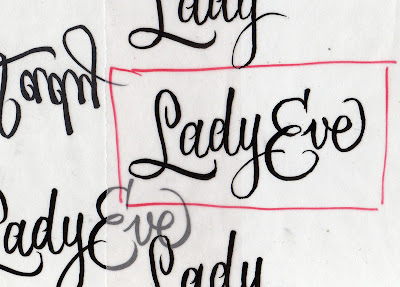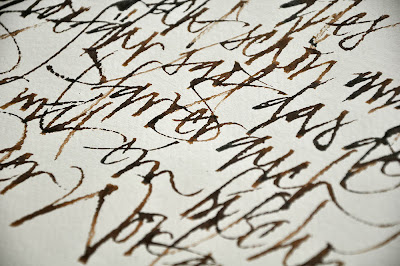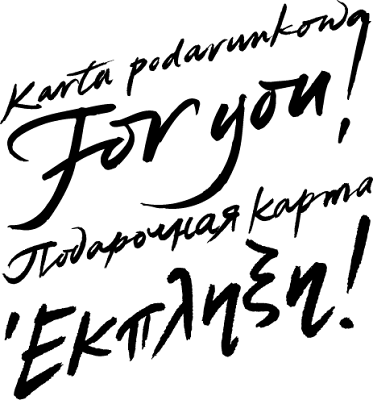
Poemes per a una Verge
Hace un tiempo os puse una portada que había hecho con Mercedes Azúa para La Bíblia de Montserrat dentro de una colección de ediciones deluxe que realiza Publicacions de l'Abadia de Montserrat, que vino seguido de una Història de Montserrat. Pues bien, siguiendo la misma idea, se ha publicado Poemes per a una Verge.
Así como en La Bíblia optamos por una mayúscula más monumental, en este caso, al ser un título más largo y al mismo tiempo el tema ser más íntimo, decidimos hacer el título en una minúscula humanista, de ejecución compleja, casi tipográfica. De todos modos, sigue siendo caligrafía, y aunque la estructura y el trazo sean precisos (está lleno de manipulaciones de la pluma), he buscado una textura imperfecta a través del papel, para dar una sensación más cálida. De alguna manera, es bastante continuista con La Bíblia e Història.
Tarjeta regalo Oysho
Si no acabas de entender de tallas de ropa interior femenina, Oysho te da la opción de regalar una tarjeta con euritos para gastar en sus tiendas. Y en extra! fuimos los encargados de diseñar la tarjeta y todas las piezas de alrededor.
Lo divertido del asunto es que como Oysho tiene presencia en todo el mundo, había que escribir estos elementos en un montón de idiomas, y esto incluye el alfabeto cirílico y el griego.
Mixohana
A raíz de la primera edición de la Faux-Tropical Bar School surgió una especie de "hermandad" internacional de cocteleros tropicales llamada Mixohana. Es difícil de definir, pero creo que captáis la idea. El caso es que para una reunión del selecto club en una fiesta privada en Amberes, el organizador me pidió un logotipo para el grupo.
Como podéis imaginar por el tema (recordad, coctelería tropical), la elegancia no es uno de los primeros factores a tener en cuenta a la hora de plantear este logo. Así que me fijé en algunos menús de los 60 de bares tropicales para llegar a la solución final. Os muestro también una foto de parte de la familia para que os ambientéis. Aloha!
Tatuaje Lady Eve
Lady Eve quería un tatuaje con su nombre. Así que mientras estábamos por ahí de vacaciones, sin ordenadores ni nada, me puse a ello. Partiendo de una caligrafía a pincel en plan publicidad años 50, amplié y redibujé para acabar de definir el dibujo que le pasaríamos al tatuador. Debería ser algo sencillo porque amigos, tatuar en la muñeca no es cosa fácil.
Aquí podéis ver el resultado final, obra de General Luis de Trashville Tattoo.
Experiencias Torres
Bodegas Torres, además de tener una amplísima gama de productos, tiene una serie de espacios que ofrecen para eventos. Este servicio se llama Experiencias Torres. En extra! nos encargamos tanto de la imagen como del dossier de presentación de la propuesta.
El logotipo está hecho con una caligrafía de pincel gestual pero aún legible aplicada sobre el logotipo de Torres, de manera que sobre la solidez de la marca tenemos algo mucho más sensual y humano, en relación a la idea de experiencia.
Del estilo de caligrafía del logotipo surgió la idea de, en la presentación, lanzar frases evocadoras que acompañaran a las imágenes de los espacios.
Clases de lettering en IED Madrid
Hace unas semanas estuve en el IED Madrid dando unas clases dentro de su Curso de Especialización de Diseño de Tipografía. Eran unas clases de lettering que sirvieran de puente entre las clases de caligrafía de Oriol Miró y las de dibujo vectorial de Josep Patau (por cierto, dos grandes tipos y amigos míos).
Soy de la opinión que a hacer cosas se aprende haciéndolas. Así que desde el primer momento nos pusimos manos a la obra a dibujar letras con un objetivo muy concreto: diseñar a mano un logotipo para un grupo de música que el azar se encargó de asignar a cada alumno. Lo interesante del tema es que puede que te toque un grupo o músico del que seas fan o puede que no lo conozcas de nada, con lo que tienes que meterte en un universo estético ajeno a tus gustos para obtener un buen resultado.
Os pongo muestras de algunos de los trabajos. Podéis ver más imágenes en el blog del curso. Es la primera vez que hago este taller y la verdad es que estoy muy contento con los resultados obtenidos, juzgad vosotros mismos.
Fernando Fuentes
Giuseppe de Cesare
Juanjez
Yago Bolívar
Cartel Mercademostraciones
Este cartel lo hicimos en extra! hace unos cuantos años, pero me cae especialmente simpático porque es de mis primeros experimentos con el pincel. Las Mercademostraciones son un evento de Mercabarna para profesionales de la floristería. Cada año trata sobre un tema, y en esta ocasión el argumento era el color.
Entonces, el diseño iba a ir de manchas de color, así que la idea era tratar el texto como una textura que se relacionara con las manchas cromáticas de acuarela. De ahí la técnica del pincel. Y el texto son los nombres de los colores primarios y secundarios en català. La pieza es un folleto desplegable, que por una cara tiene toda la información sobre el evento y por la otra es el cartel.
Lastig
Rae Doornik es una artista multidisciplinar de Amsterdam que tiene un proyecto nuevo llamado Lastig. Dado el secretismo del tema, que está en proceso de gestación, la artista se negó a darme más datos, pero me dijo que debería tener un aspecto en plan cholo angelino. Rae vivió un tiempo en California y algo le quedó de eso. Así que llegué a este logo, basado en una gótica y con este recurso del sombreado que recuerda al graffiti y a los tatuajes, pero manteniendo una cierta legibilidad.